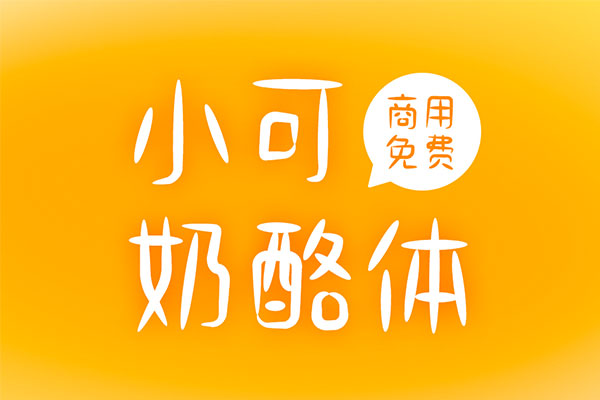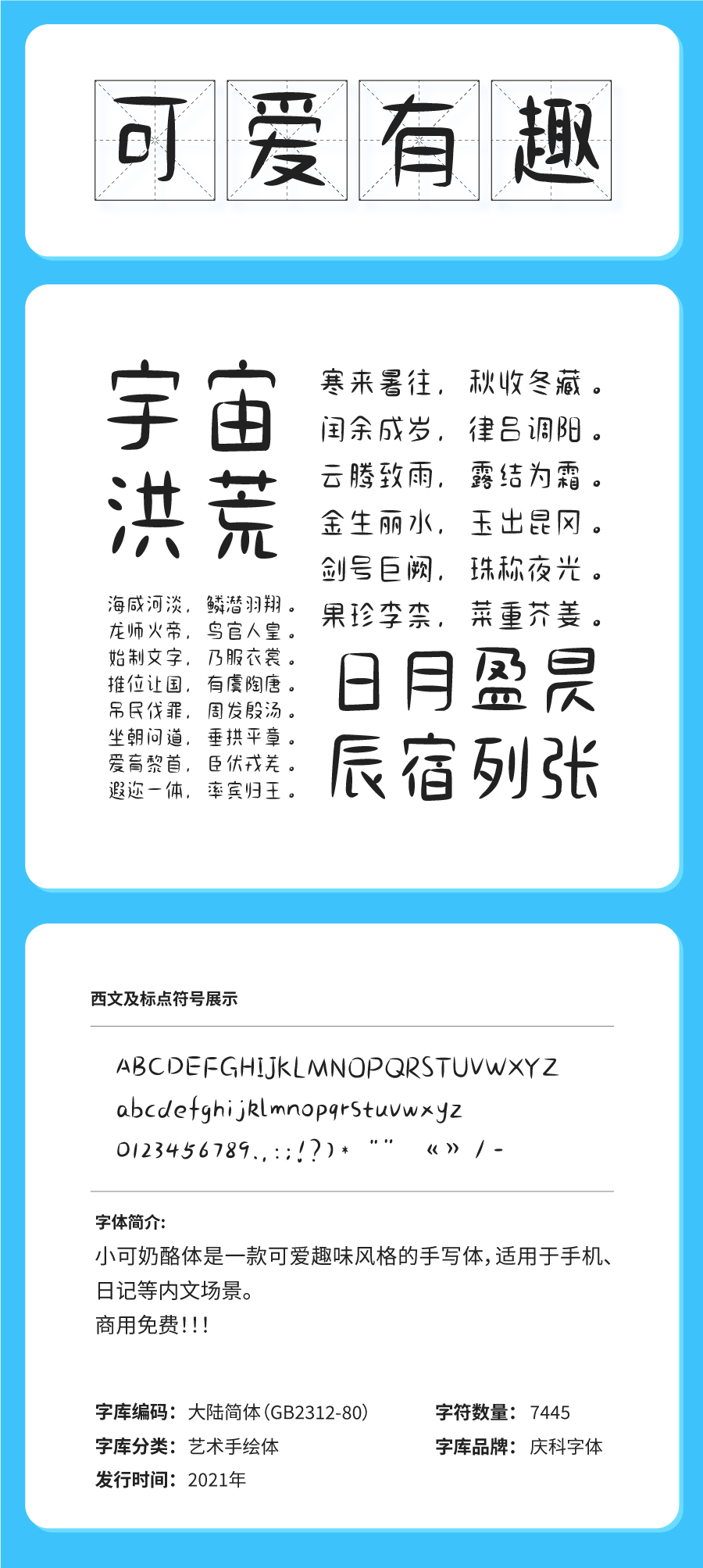
小可奶酪体
小可奶酪体:一款充满可爱趣味的手写风格艺术字体
小可奶酪体,这款备受关注的新字体,是国内知名字体设计师郑庆科的又一力作。作为自由字体已收录的庆科FS霓虹灯英文体、站酷庆科黄油体、创客贴金刚体的创造者,郑庆科凭借其独特的创作风格和敏锐的设计洞察力,再次为我们带来了一款极具设计感的免费商用字体。
小可奶酪体以其手写风格为特点,整体字形流畅自然,轻松随性。每个字形都仿佛是一位活泼可爱的孩子在纸上留下的随意涂鸦,充满了趣味性和艺术性。